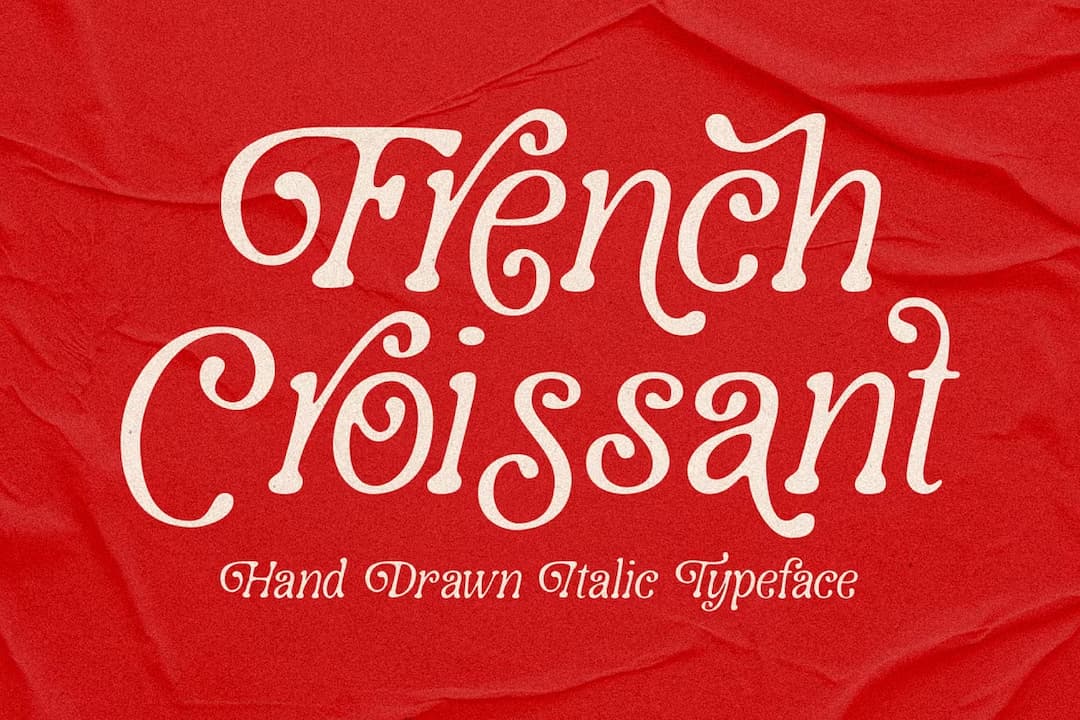
軽やかで可愛らしいソフトセリフイタリック。ライトウェイトのストロークに丸いセリフがぽてっと付いた書体で、スクリプトに見えるがまあ(活字の)イタリックであろう。あちこちカールしたスワッシュが付いているがこれはデフォルトでそうなっているので、大人しくさせるのは不可能である(笑)。ただちゃんと統制は取れてるので、作者の腕のほどが伺える。全体的な雰囲気はポップでガーリー。名前も「フレンチクロワッサン」と可愛らしくセンスがある。クリスマスにもよく似合うだろう。1ウェイトのみ。